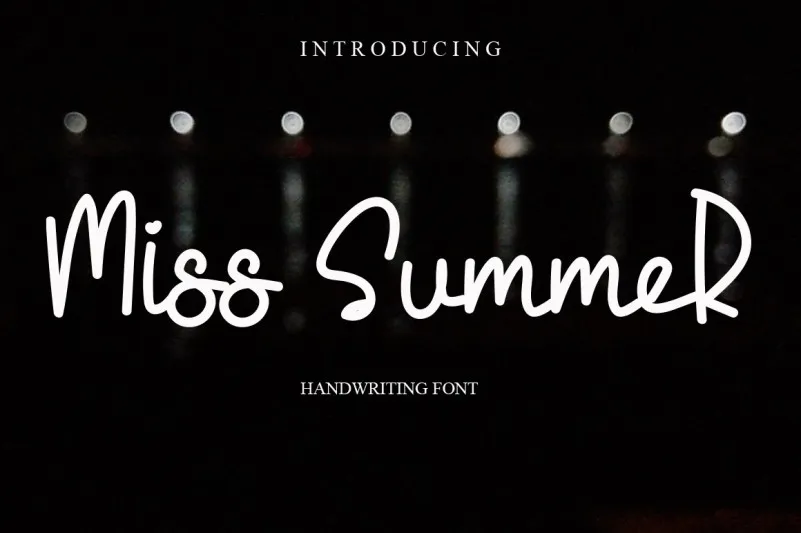
Miss Summer Font – Download Grátis
A Miss Summer Font é uma fonte escrita à mão única e encantadora que adorarás incorporar em projetos pessoais ou comerciais sem comprometer a sua personalidade. Perfeita para quem busca um tom descontraído mas assertivo, essa fonte é ideal tanto se você está buscando uma ideia de como usar o seu Instagram na melhor forma, quanto para projetos DIY que precisam de um toque cuidadosamente elaborado e amigável. Seja ela a base de um projeto de marca personalizada ou até mesmo de cartões de aniversário, essa fonte transforma qualquer conceito criativo em arte genuína. E embora não seja inventada de forma alguma, é com certeza uma escolha que vai revolucionar como você usa o seu design no mundo digital e físico.